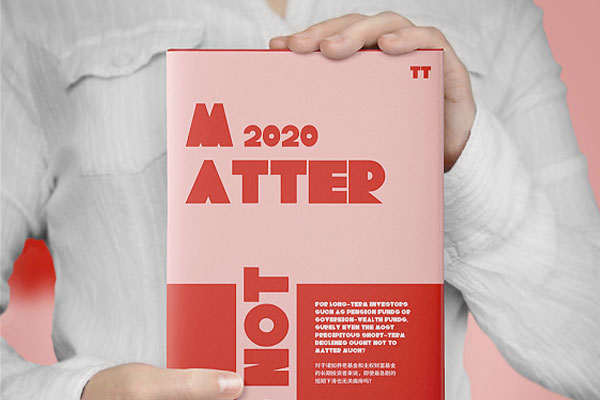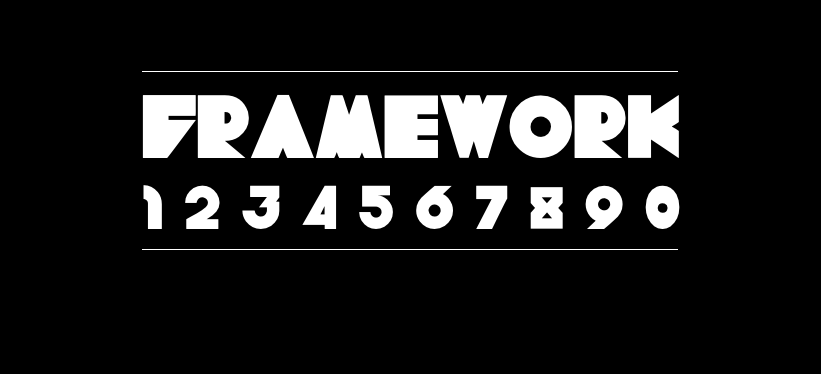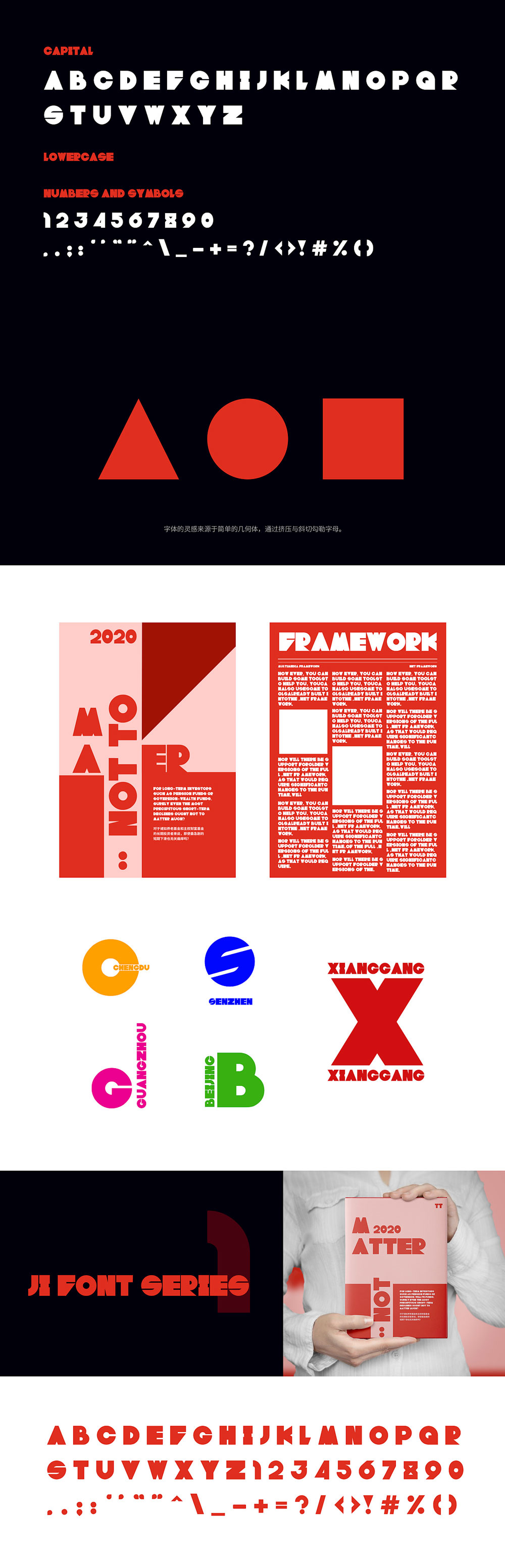
Framework
Framework字体介绍
Framework的作者是来自中国湛江的学生叶伟鹏(特立独行的小鹏),该字体是叶伟鹏同学的第一款练手字体,字形新锐大胆,非常霸气,而且作者还在读大学,自由君不禁感叹人与人的差距怎么这么大,自己的大学算是白读了。Framework字体首发于站酷,作者声明免费商用。
Framework字体应用示例